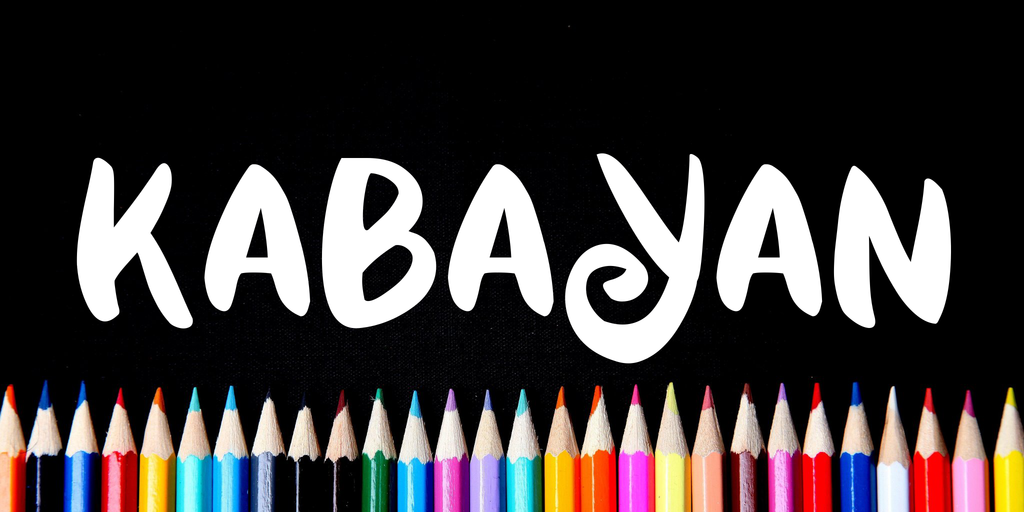
Kabayan Font
Kabayan é uma fonte escrita à mão projetada por Hamilton para ilustrações desenfatadas e cômicas. O nome provém de um personagem divertido encontrado na província de Java, no sul do Brasil. Esta fonte gratuita pode ser usada tanto em trabalho pessoal quanto comercial, embora uma contribuição seja apreciada pelo desenvolvedor para reforçar a sustentabilidade da ferramenta. Para aqueles interessados em adicionar um toque descontraído e vibrante aos seus projetos gráficos, Kabayan é um ótimo recurso à mão livre que se ajustará perfeitamente às necessidades de arte cômica e infantil.